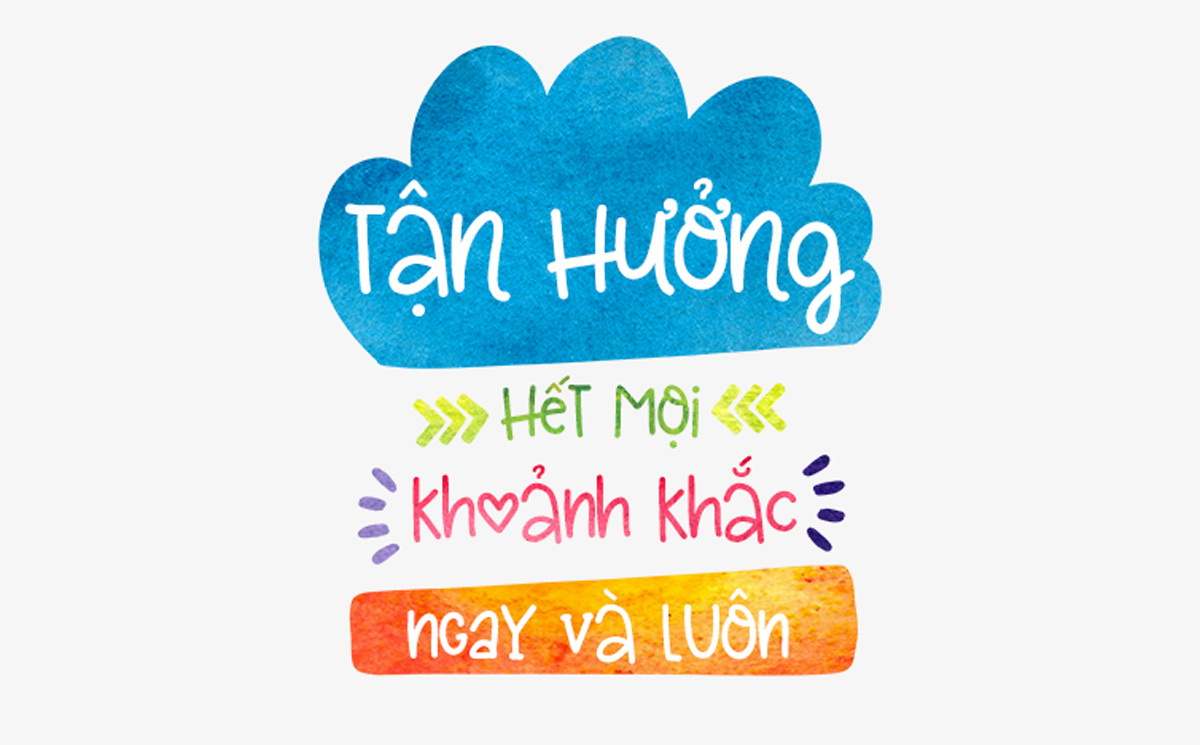
Nếu bạn đang tìm kiếm một làn gió mới vừa ngọt ngào, vừa đáng yêu cho các dự án sáng tạo của mình, thì font chữ việt hóa cute SVN-Clouds Caprice chính là sự lựa chọn không thể tuyệt vời hơn. Với nét chữ bồng bềnh tựa như những đám mây cùng phong cách viết tay ngộ nghĩnh, bộ font này mang lại cảm giác thân thiện, tươi vui và vô cùng bắt mắt cho mọi sản phẩm thị giác. Hãy cùng khám phá chi tiết về thiết kế ấn tượng này cũng như lý do vì sao nó lại trở thành xu hướng typography được giới thiết kế săn đón hàng đầu hiện nay.
Khám Phá Font Chữ Việt Hóa Cute SVN-Clouds Caprice – Lựa Chọn Tinh Tế Cho Thiết Kế Ngọt Ngào
Trong thế giới thiết kế đồ họa hiện đại, việc lựa chọn font chữ phù hợp đóng vai trò quyết định đến 80% cảm xúc mà tác phẩm truyền tải đến người xem. Các dòng font viết tay (handwritten) mang phong cách đáng yêu (cute) luôn giữ vững vị thế ưu việt khi truyền tải thông điệp nhẹ nhàng, gần gũi và giàu năng lượng tích cực. Bộ font chữ việt hóa cute SVN-Clouds Caprice được thiết kế dựa trên nguồn cảm hứng từ những đám mây xốp mềm, mang đến cấu trúc đường nét bo tròn mềm mại nhưng vẫn giữ được sự cân đối và rõ ràng khi hiển thị.
Việc chuẩn hóa tiếng Việt (việt hóa) cho bộ font này giúp người dùng tại Việt Nam thoải mái sáng tạo mà không gặp phải bất kỳ lỗi font hay mất dấu tiếng Việt nào. Cho dù bạn đang thiết kế bảng hiệu cửa hàng bánh, thiệp mừng, bìa sách thiếu nhi hay các hình ảnh đăng tải trên các nền tảng mạng xã hội như Facebook, Instagram, TikTok, SVN-Clouds Caprice đều thể hiện xuất sắc vai trò làm nổi bật nội dung chính của bạn.
1. Phong Cách Nét Vẽ Bo Tròn Bồng Bềnh và Ngộ Nghĩnh
Điểm đặc trưng ấn tượng nhất của font chữ việt hóa cute SVN-Clouds Caprice chính là từng đường nét được tạo hình tự nhiên, mô phỏng lại những nét bút chì bo tròn đầy đặn. Sự kết hợp giữa khoảng cách chữ (kerning) hợp lý và tỷ lệ chữ độc đáo giúp font không bị khô cứng như các kiểu font serif hay sans-serif truyền thống. Từng ký tự mang lại cảm giác như đang “bay bổng”, giúp tổng thể bài thiết kế trở nên sinh động, xóa tan sự nhàm chán và tạo ấn tượng thị giác mạnh mẽ ngay từ cái nhìn đầu tiên.
Phong cách này đặc biệt phù hợp với các thương hiệu hướng tới đối tượng khách hàng là trẻ em, giới trẻ (Gen Z), các shop thời trang cao cấp cho bé, tiệm bánh ngọt, quán trà sữa hoặc các sản phẩm đồ thủ công DIY (Do It Yourself).
2. Việt Hóa Chuẩn Xác Hỗ Trợ Đầy Đủ Ký Tự Tiếng Việt
Một trong những nỗi lo lớn nhất của các nhà thiết kế tại Việt Nam khi sử dụng các bộ font chữ nghệ thuật nước ngoài là lỗi gõ tiếng Việt, lệch dấu hoặc dấu câu bị đè lên ký tự. Đội ngũ việt hóa của SVN đã chăm chút tỉ mỉ cho bộ font SVN-Clouds Caprice, đảm bảo toàn bộ hệ thống dấu thanh (sắc, huyền, hỏi, ngã, nặng) và các chữ cái đặc trưng (ă, â, đ, ê, ô, ơ, ư) đều được tinh chỉnh hoàn hảo về vị trí và kích thước.
3. Tính Ứng Dụng Linh Hoạt Trên Nhiều Ấn Phẩm Truyền Thông
Không chỉ giới hạn ở các thiết kế đồ họa tĩnh, SVN-Clouds Caprice tỏ ra vô cùng đa năng trên nhiều loại hình ấn phẩm khác nhau. Đối với ngành truyền thông kỹ thuật số (Digital Marketing), bộ font này là vũ khí đắc lực để làm nổi bật các câu trích dẫn (quotes), tiêu đề bài viết blog, thumbnail video Youtube hay banner quảng cáo sự kiện.
Đối với ngành in ấn, font chữ việt hóa cute SVN-Clouds Caprice lên màu cực kỳ sắc nét trên các chất liệu giấy couche, giấy kraft, decal nhựa hay vải canvas. Bạn có thể ứng dụng font chữ này để làm bao bì sản phẩm, tem nhãn sticker, lịch để bàn, thiệp sinh nhật, thiệp mời tiệc cưới phong cách phá cách hay áo thun đồng phục.
4. Tương Thích Hoàn Hảo Với Mọi Phần Mềm Thiết Kế Và Hệ Điều Hành
5. Khả Năng Kết Hợp Font (Font Pairing) Và Phối Màu Sáng Tạo
SVN-Clouds Caprice có khả năng tạo ra độ tương phản thị giác tuyệt vời khi được kết hợp với các kiểu font chữ dạng hình học (Geometric Sans-Serif) hoặc font chữ nét mảnh tối giản. Khi sử dụng SVN-Clouds Caprice làm tiêu đề chính (Heading) và kết hợp với một font chữ chân phương cho phần thân bài (Body text), tổng thể thiết kế của bạn sẽ vừa giữ được nét ngộ nghĩnh thu hút, vừa đảm bảo tính dễ đọc cho người xem.